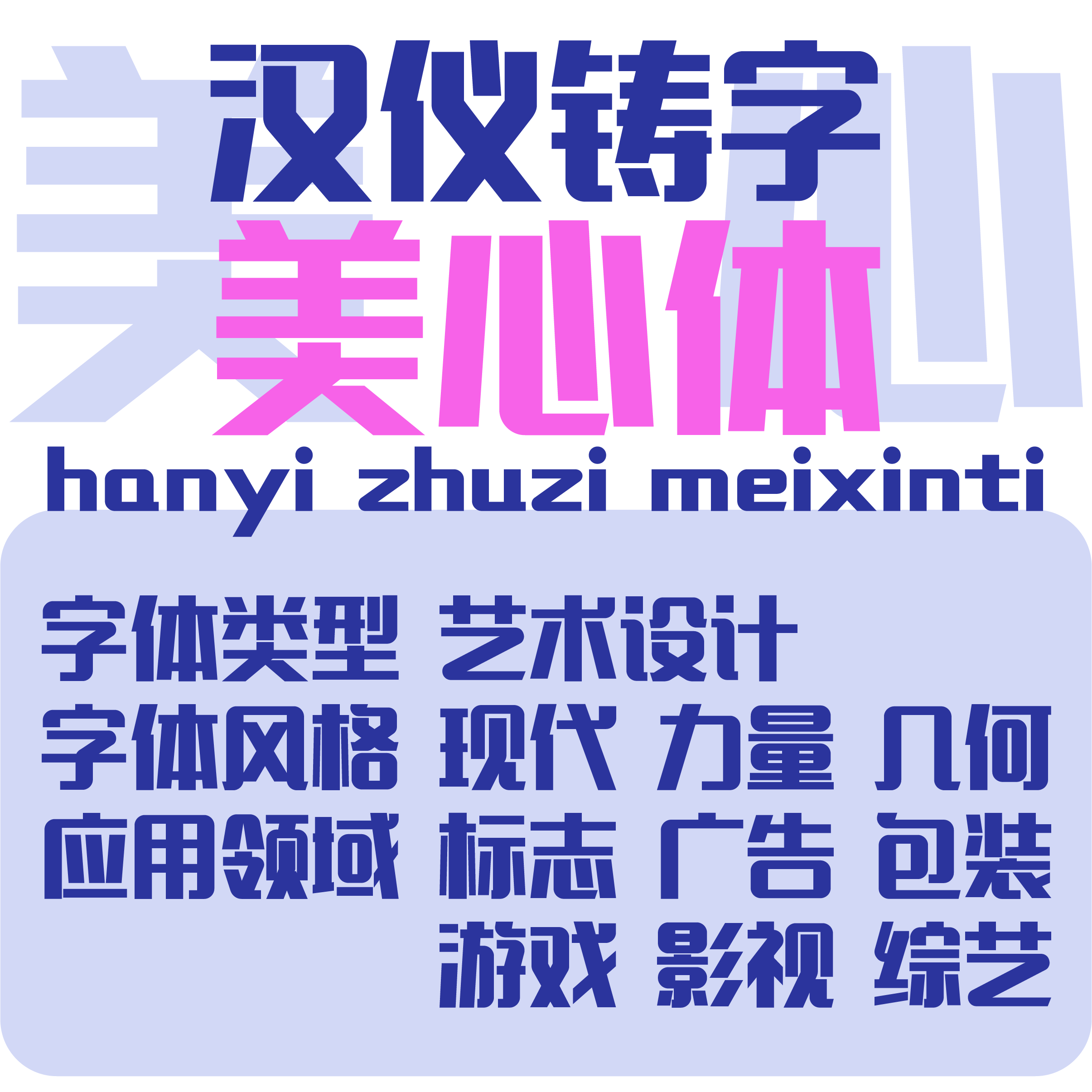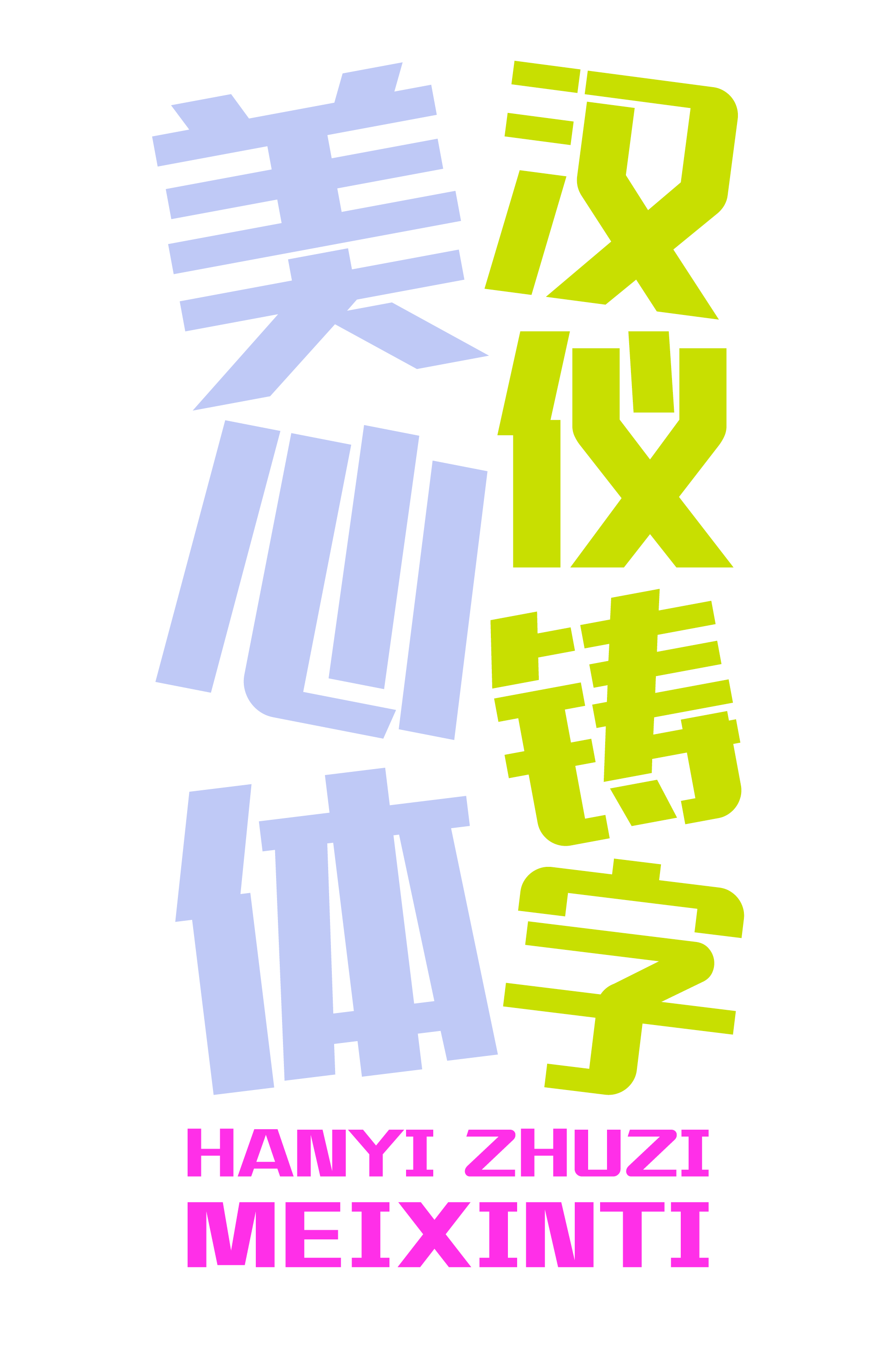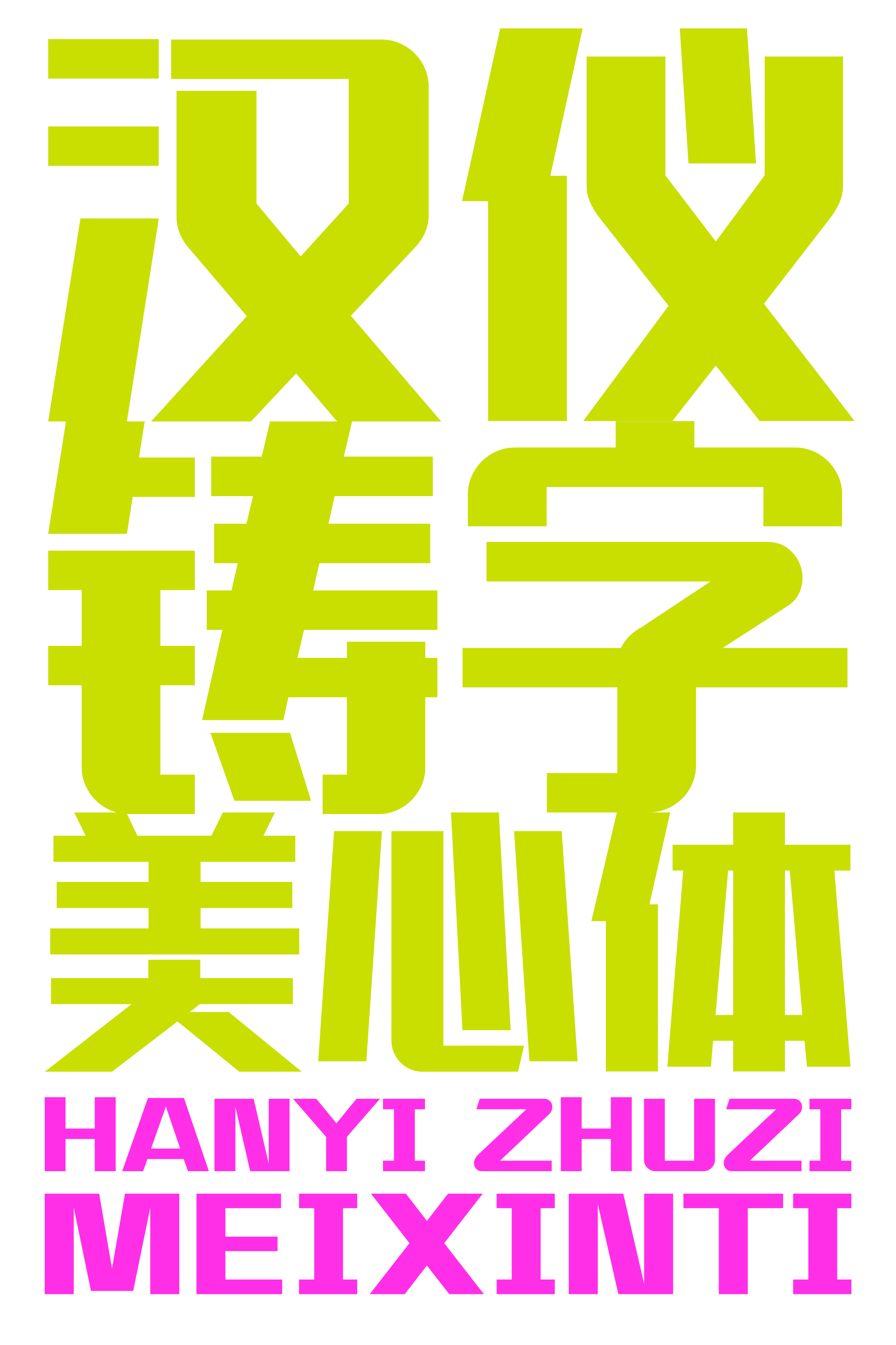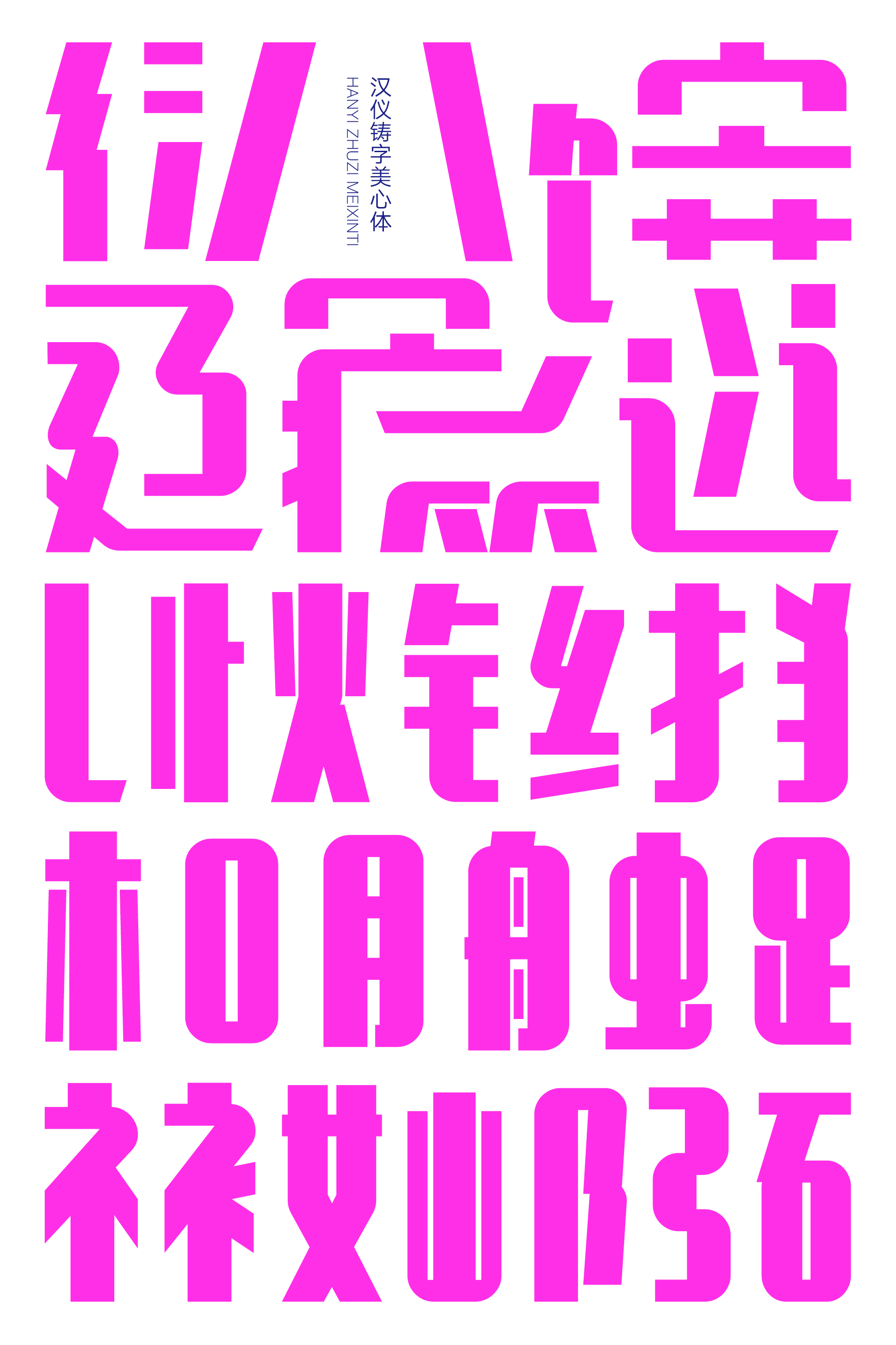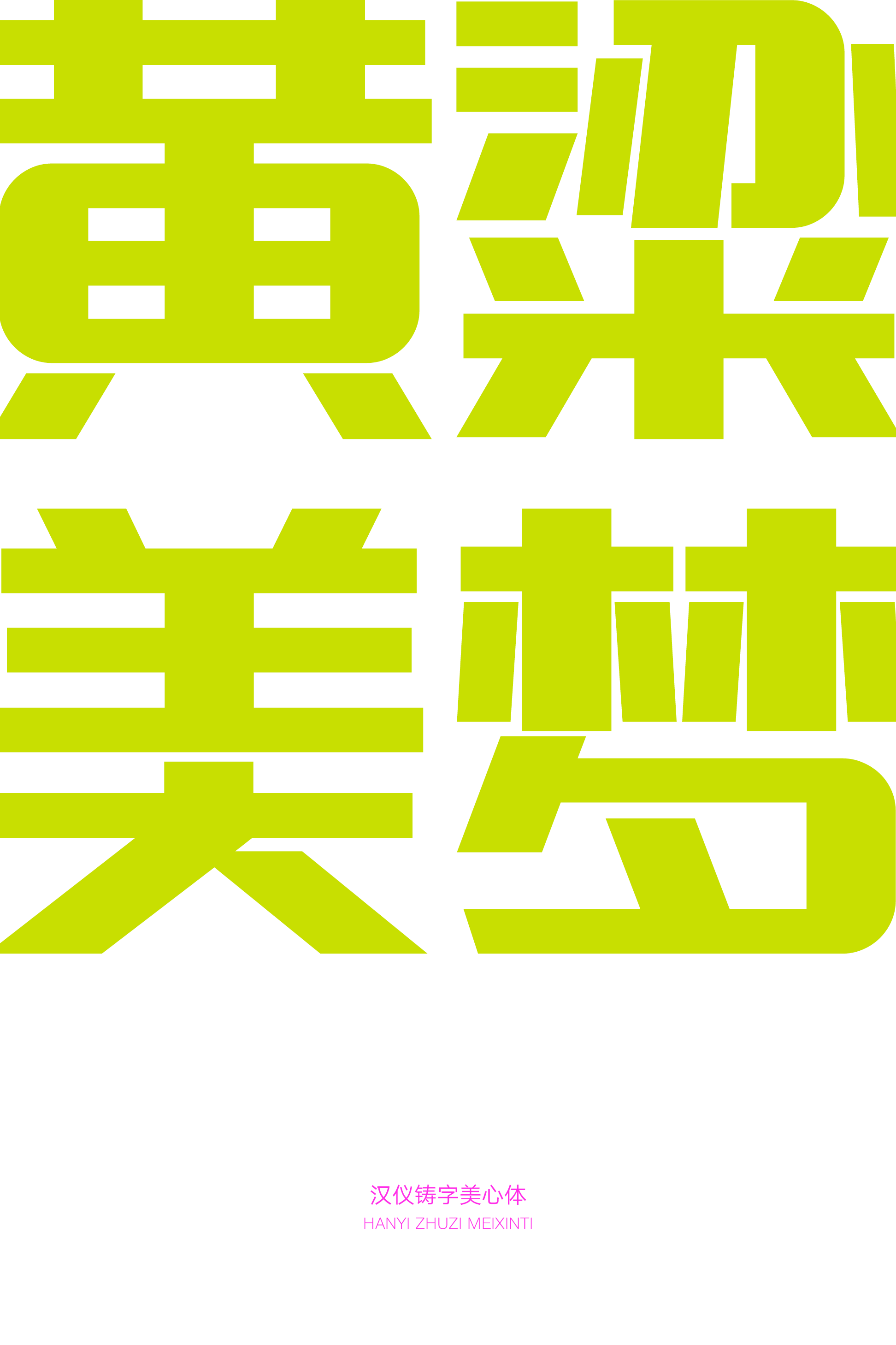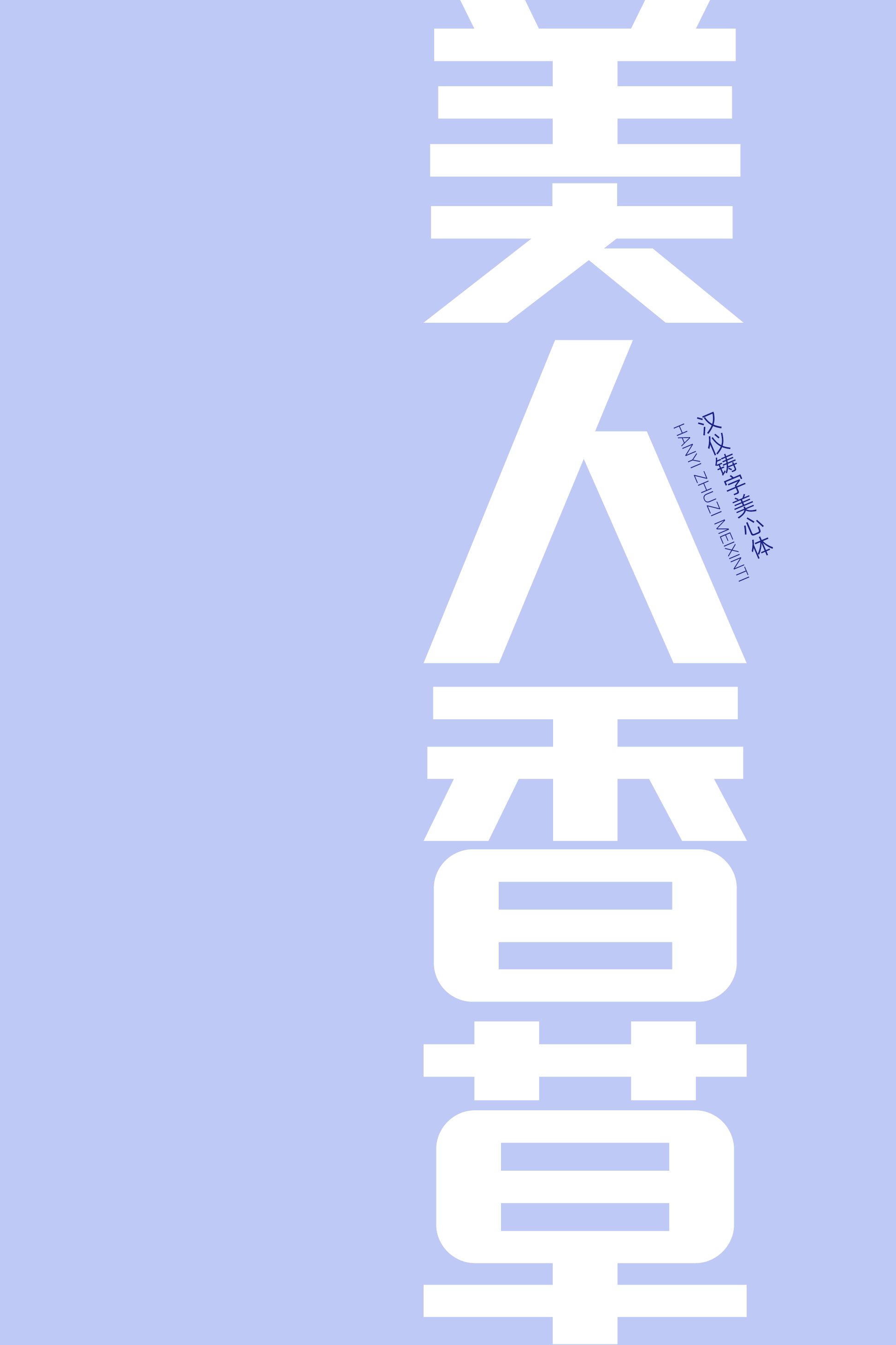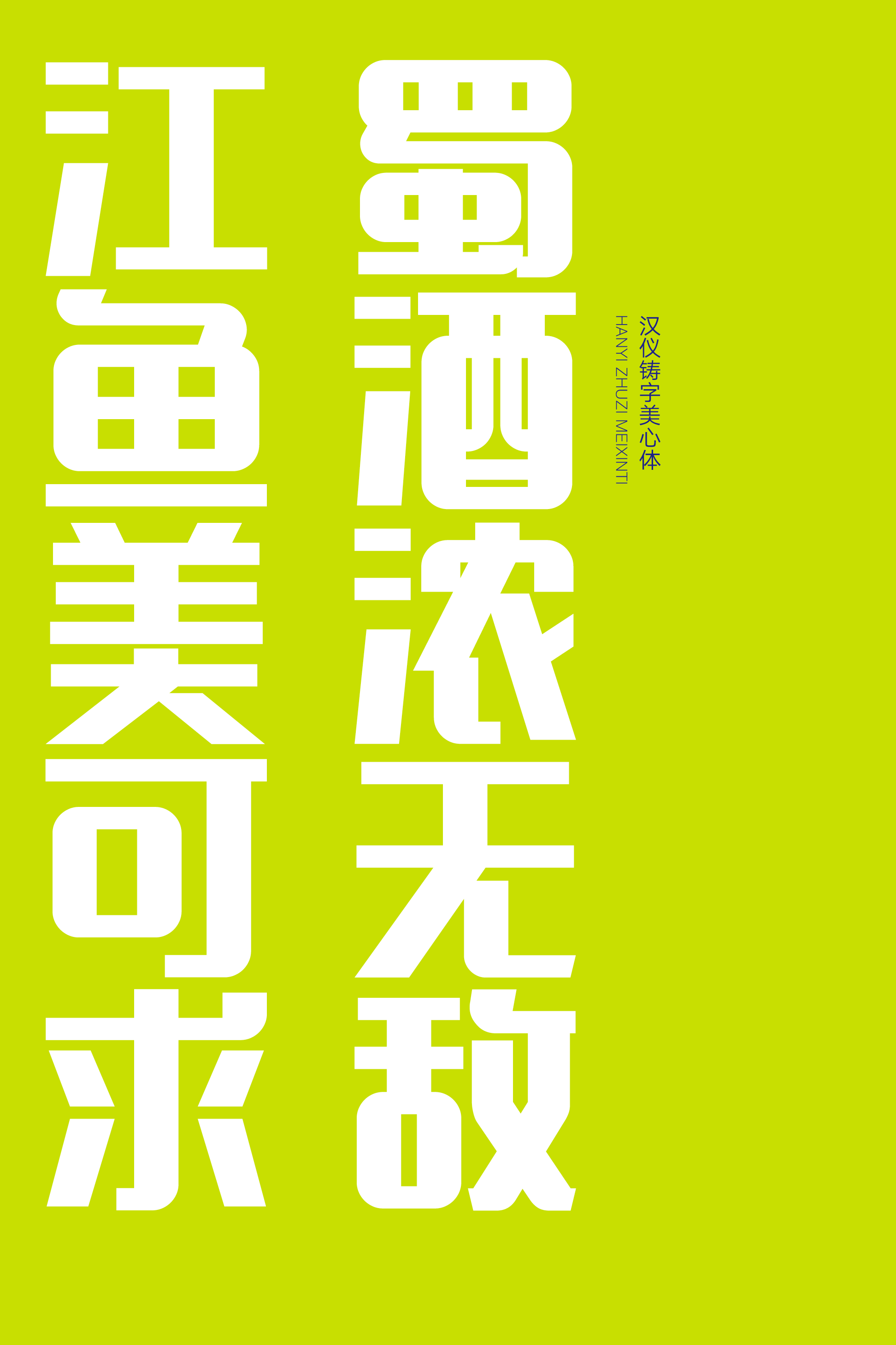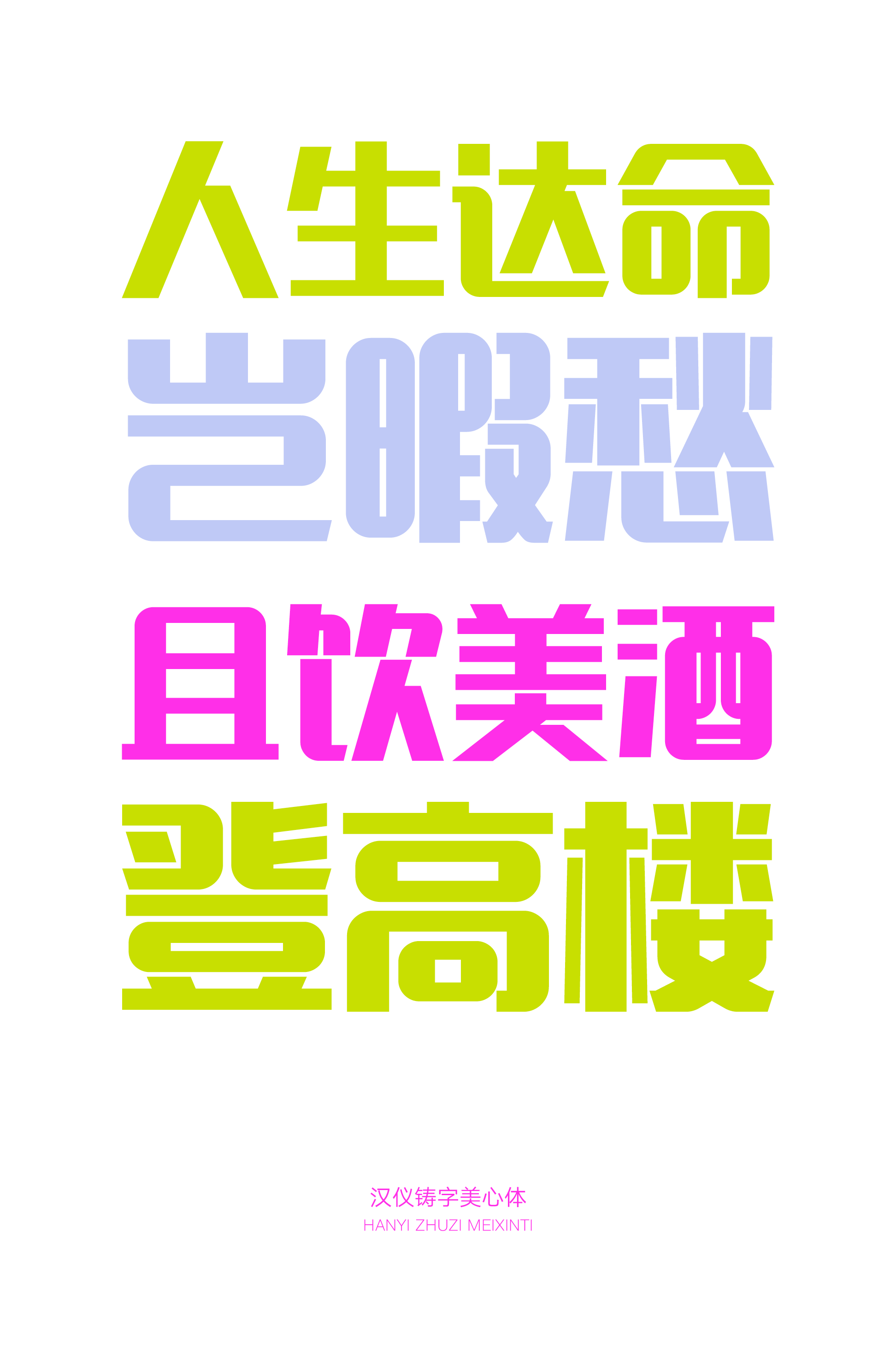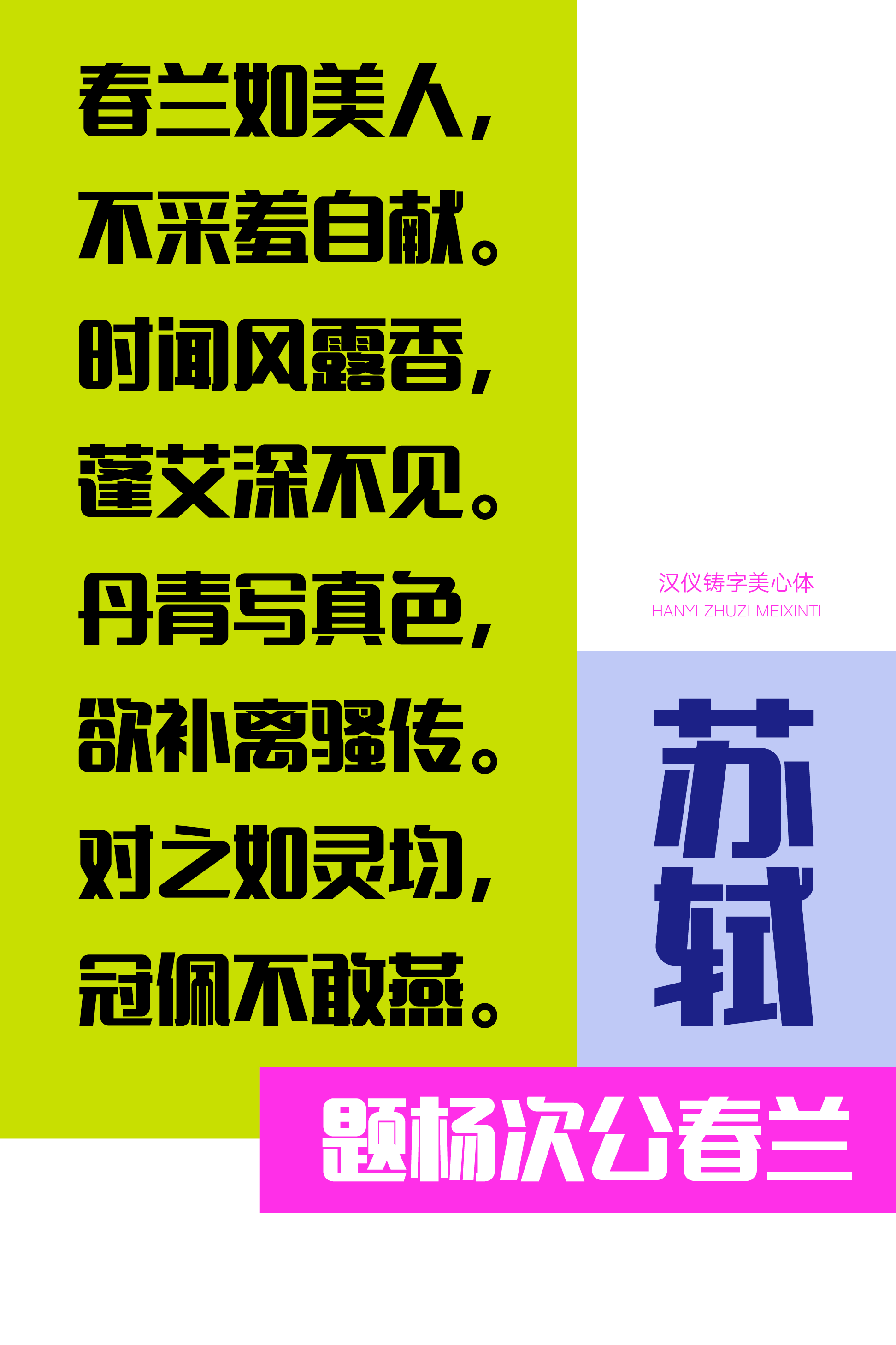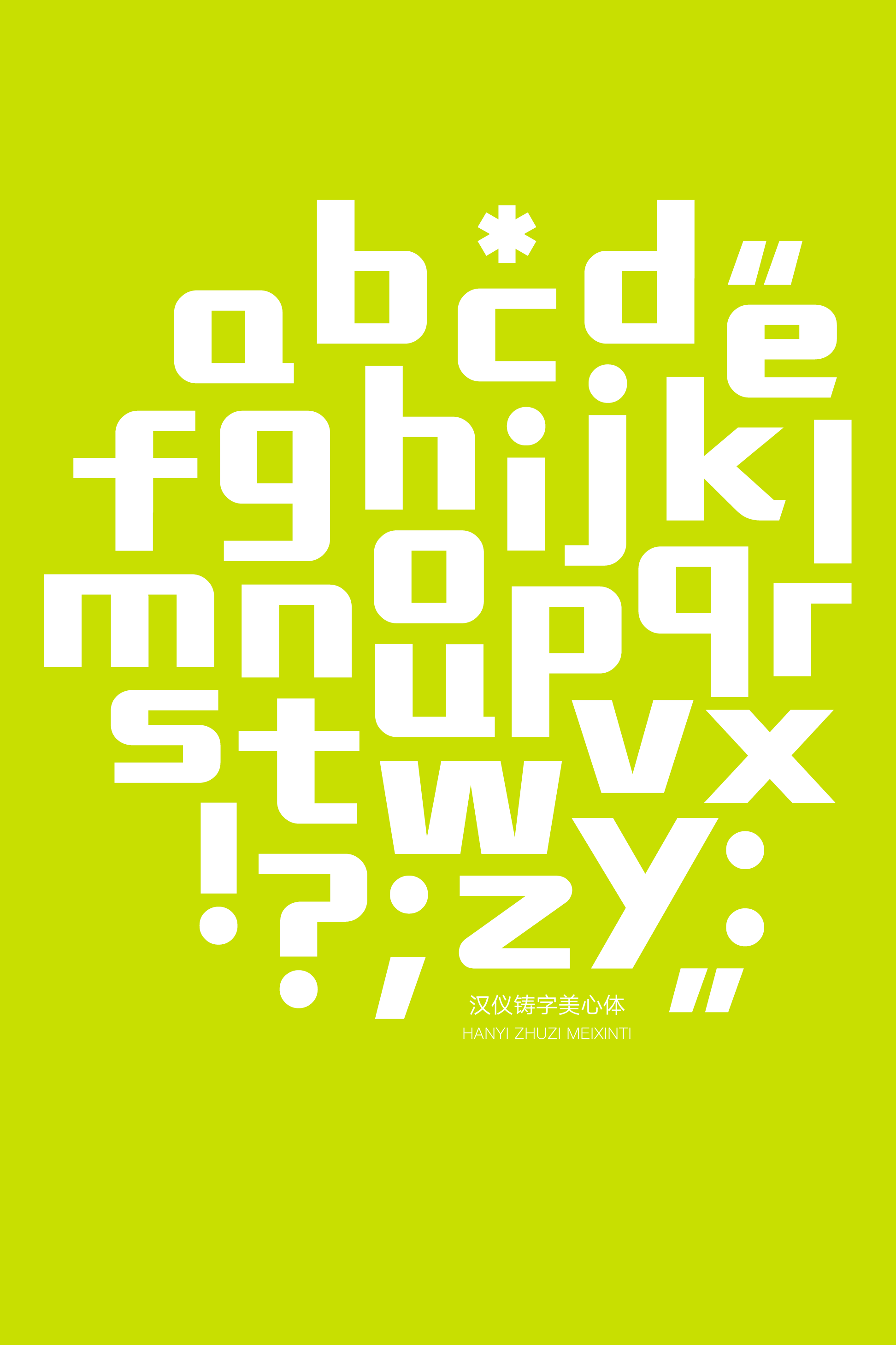
汉仪铸字美心体
汉仪铸字美心体,外圆内方,刚柔并济,是一款“语气”亲切友好的标题美术字。造型呈矩形,中宫满而外扩,笔画粗细均匀,在可控范围内向最大限度舒展,并作简化连接处理。汉仪铸字美心体适合用于潮流时尚品牌的标识和包装、食品餐饮类广告、影视综艺节目的标题和花字等使用场景。
字形呈圆角矩形,中宫满而外扩。
笔画外圆内方,粗细均匀,在可控范围内向最大限度舒展。
部分笔画作简化连接处理,形成流畅的曲线。
西文部分保持一致的简约造型,外圆内方,时尚大气。